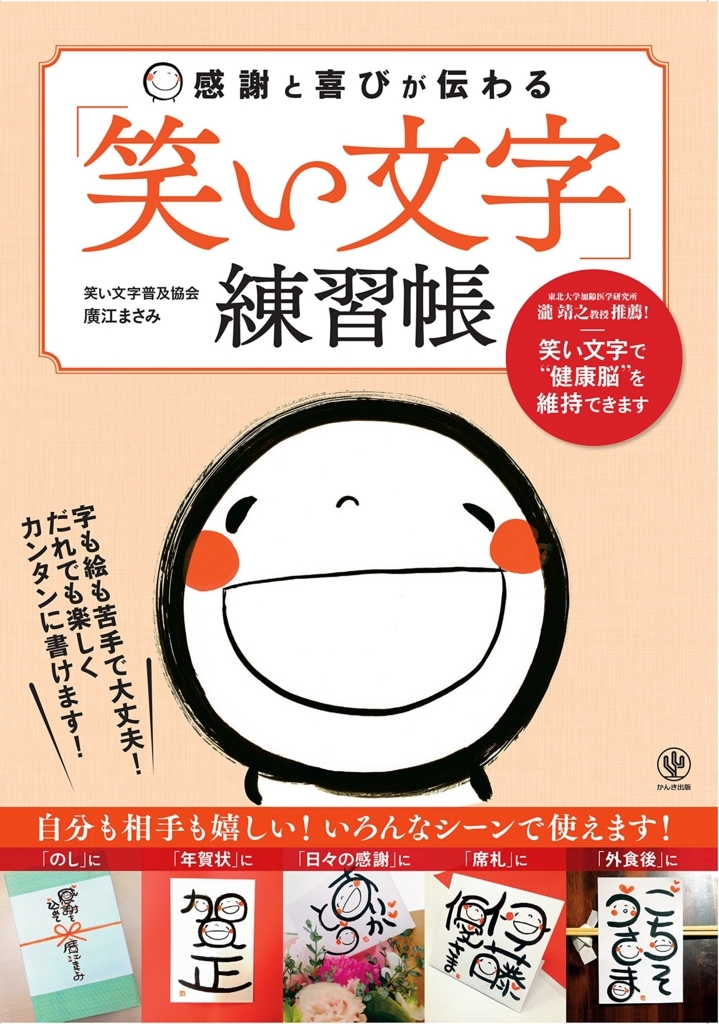
感謝と喜びが伝わる「笑い文字」練習帳
笑い文字のメソッドを確立した廣江まさみによる、字も絵も苦手でも誰でも楽しく簡単に「笑い文字」を上達させる練習帳『感謝と喜びが伝わる「笑い文字」練習帳』が、かんき出版から2018年5月11日に発売される。
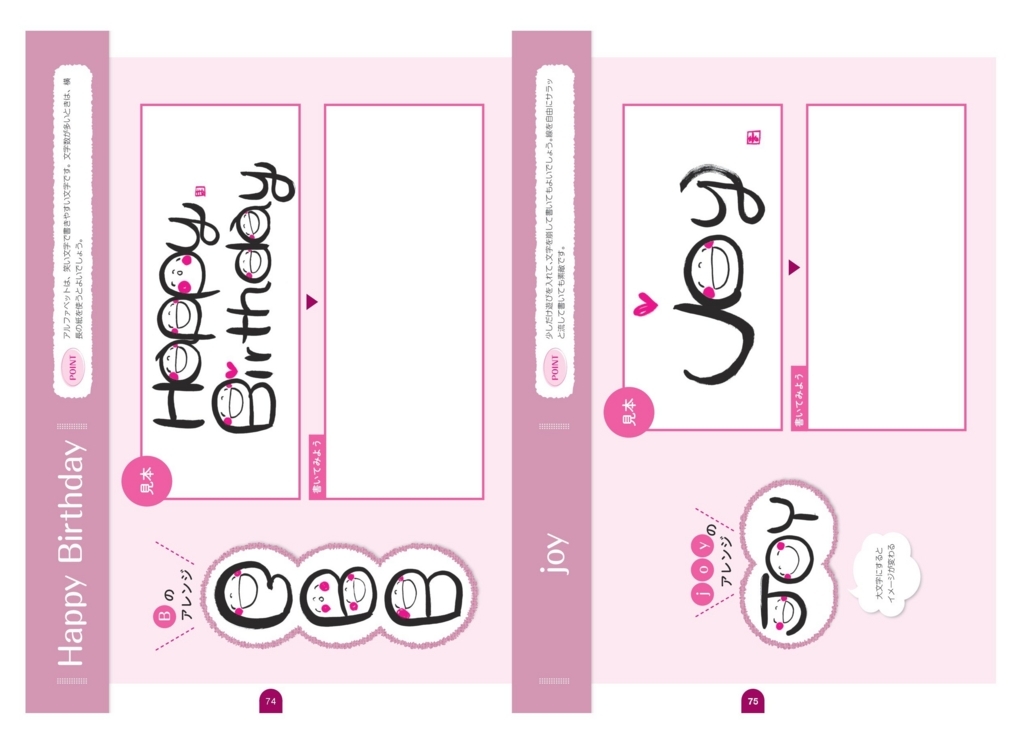
16万人の脳画像を見てきた脳医学者・瀧 靖之氏推薦!
「笑い文字で“健康脳"を維持できます」
字も絵も苦手で大丈夫! だれでも楽しくカンタンに書けます!
「笑い文字」は、書いて半分、渡して完成。
差し上げた人も、もらった人も幸せになれる、満面の笑顔のコミュニケーションツールです。
書いて渡すことで、感謝や喜びを日常のなかに見つけたり、 人間関係が豊かになったり、ずっと幸せな毎日がつづくということに気がついたりします。
~「笑い文字」を書いて渡した人の声~
〇「笑い文字を書くようになってから、人にたくさん感謝できるようになりました」(42歳・女性)
〇「日常に、こんなにもうれしいことがたくさんあることに、はじめて気がつきました」(70歳・男性)
〇「自分が書いたもので人が感動して泣くなんて」(57歳・女性)
〇「本当につらいときにこの文字が支えになりました」(46歳・女性)
など反響多数!
~こんなシーンで使えます!~
・すぐに伝えたい感謝や想いに
・お誕生日や記念日、進学・就職、結婚・出産など、お祝いの場面に
・年賀状やお礼状、旅先から送るお手紙、季節のお便りに
・ビジネスシーン……お客様や取り引き先の方などに
廣江まさみProfile●一般社団法人笑い文字普及協会代表理事。「感謝と喜びの循環する世界を作る」を理念に、2014年6月一般社団法人笑い文字普及協会を設立。文字と満面の笑顔で構成された最強のコミュニケーションツール「笑い文字」のメソッドを確立する。創始者として、国内外での講座の開催や後進育成など、笑い文字を日本の文化として普及させる活動に尽力している。協会主催の笑い文字講座は瞬く間に全国に広がり、設立4年で講座受講者数は3万人に達する。協会ビジネス推進機構主催の協会アワード2017 にて最優秀社会貢献部門賞受賞。協会オリジナルの笑い文字専用はがき「はははがき」は、発売1年半で150 万枚を超す大ヒット商品となり、現在も好評を博している。また、日本郵便発行の笑い文字切手は、発売と同時に即完売が続き、「幻の切手」と呼ばれる。笑い文字を通して、すべての人々が自己肯定感をもち、感謝と喜びを循環させる豊かな社会をめざす。感謝と喜びを伝えたいときはもちろん、ビジネスシーンをはじめ葬儀の場面においても、笑い文字を書いて渡す文化を世界中につくりたいと願っている。
笑い文字作品集「あなたは大事な人 幸せを呼ぶ笑い文字」
廣江まさみ氏著書「あなたは大事な人 幸せを呼ぶ笑い文字」は、みらいパブリッシングから2015年10月15日に発売された。
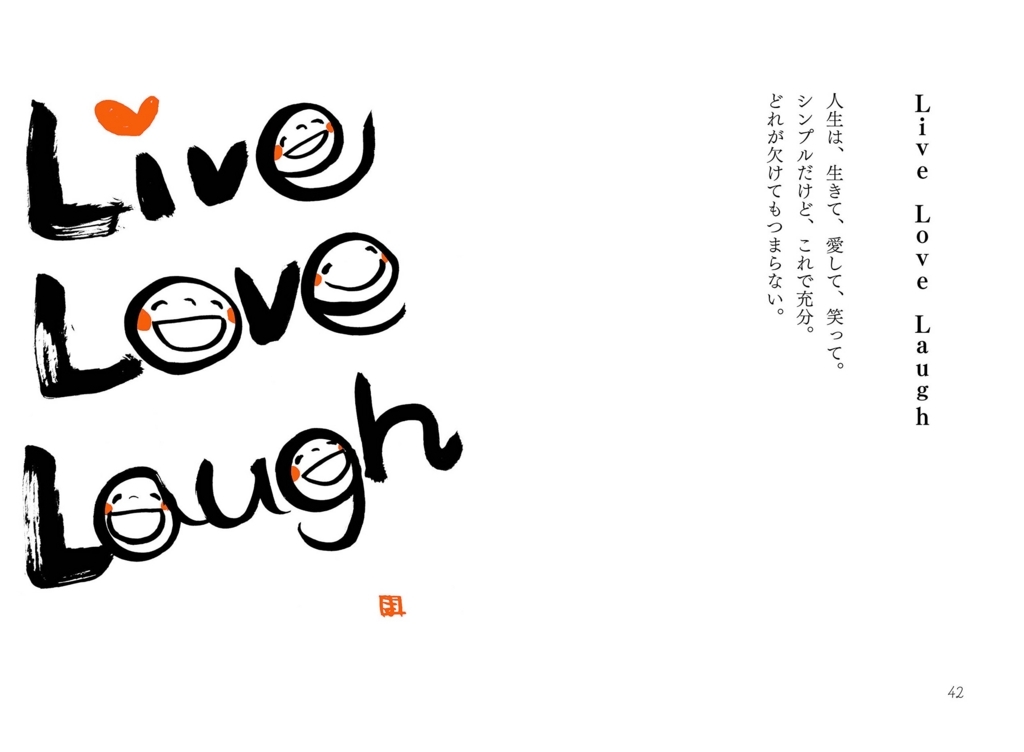
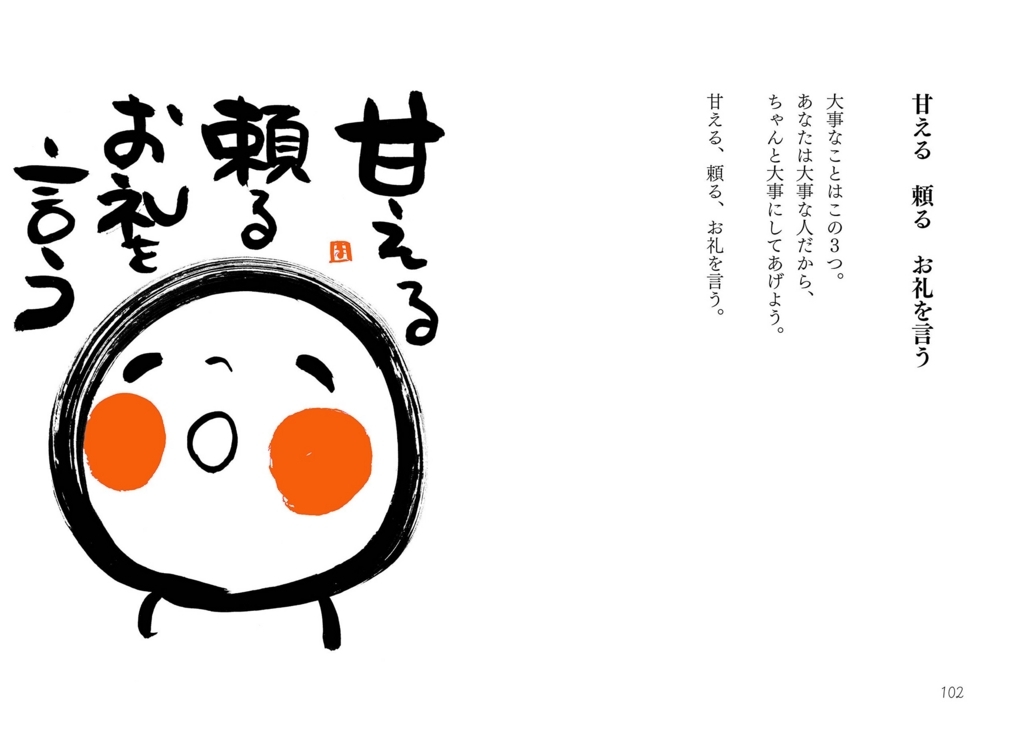
日辛い時も、おもわず笑みが溢れる
笑顔と感謝と喜びが巡る、 笑い文字
笑顔は心を結ぶ魔法!
笑い文字は、満面の笑顔の筆文字。
「書いて半分、人に渡して完成」がお約束。
あなたの大事な人にあなたから渡される笑顔と感謝と喜びは、次の人を幸せにします。
笑い文字を書いた瞬間、なぜか笑顔になる。その笑顔は、周りへと伝わっていく。世界が笑顔で溢れるきっかけになる本です。